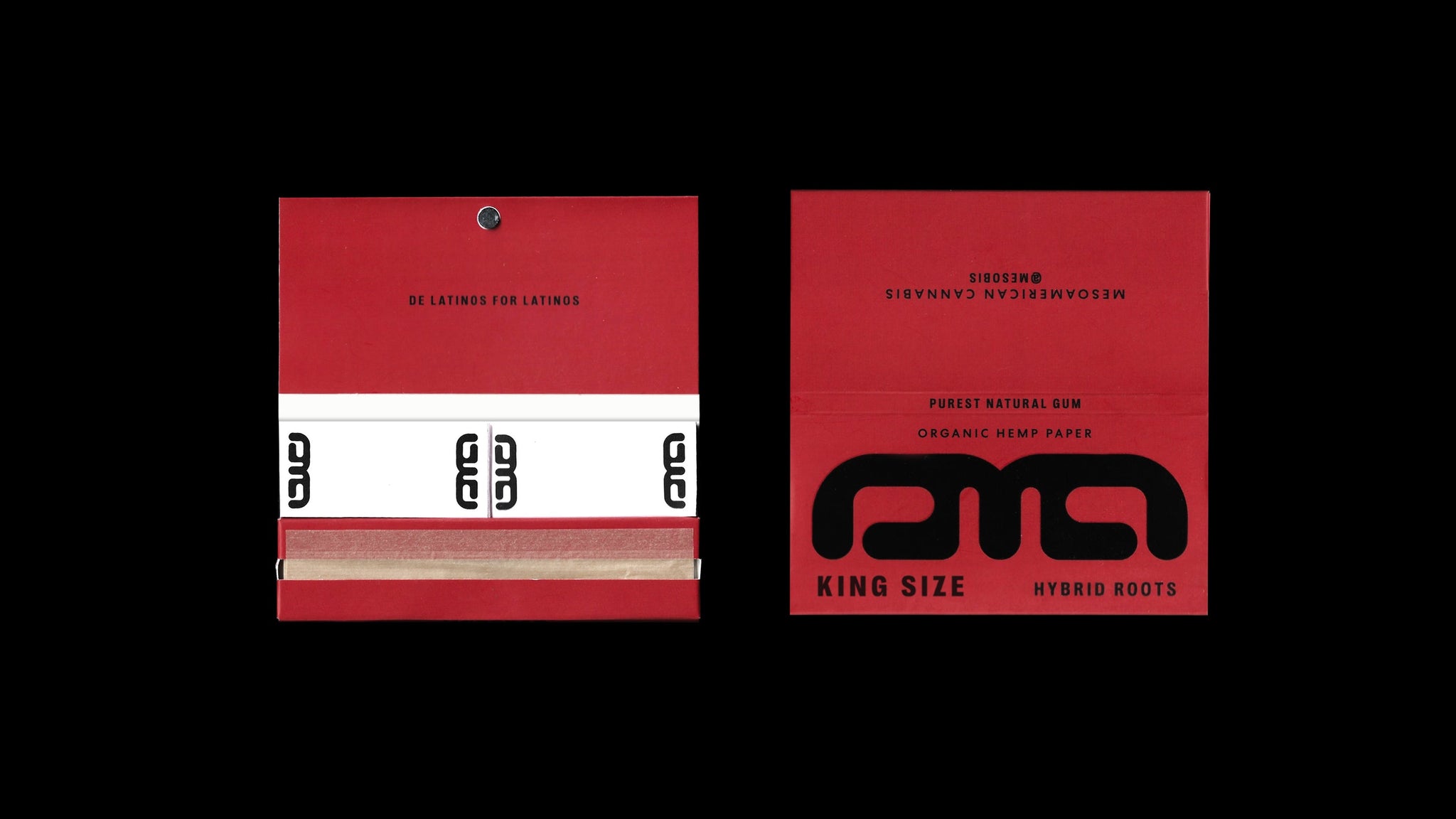
La marque de cannabis Mesobis, basée à Los Angeles, a été créée pour relier les cultures et civilisations californiennes et mésoaméricaines, en combinant des inspirations historiques et brutalistes pour raconter une nouvelle histoire puissante pour l'époque moderne.
Dans le cadre d'une collaboration basée à Mexico avec le studio de design Mad Monk, le designer guatémaltèque Andrés Higueros a entrepris d'incarner visuellement cette entreprise à travers une typographie d'influence maya et de saveur futuriste, armé d'une riche compréhension du contexte de la marque.
« Conformément aux principes de cet art », explique Higueros, en référence à ses racines latino-américaines, « j'ai choisi deux polices de caractères complémentaires », optant pour la Right Grotesk, une police sans empattement Condensede de Pangram Pangram, comme titre principal, aux côtés du logotype sur mesure, imposant et massif. « Right Grotesk s'intègre parfaitement à l'esthétique du logo », explique Higueros, suggérant l'avantage conjonctif et harmonieux de la construction audacieuse et robuste de la police. « Elle équilibre l'esthétique brutaliste de la police personnalisée du logo », poursuit-il, « et les messages de la marque, créant ainsi une marque cohérente », soutenue par l'utilisation de Centra No. 2 de Sharp Type comme police secondaire. « Centra No. 2 est une typographie géométrique qui intègre également des principes brutalistes dans son anatomie », rappelle Higueros, « mais avec une approche tendance », optimisée pour les petits formats de texte grâce à sa nature géométrique.
On retrouve un même discours de simplicité, de praticité et de narration dans la palette de couleurs de Mesobis, le designer ayant opté pour une palette vive qui permet de différencier les produits proposés. « Chaque couleur est liée aux effets du cannabis sur le corps », explique Higueros, précisant que le jaune est énergisant, le rouge passionné, le vert rafraîchissant et le rose relaxant. « Ces couleurs s'inspirent de celles que l'on retrouve dans les pays d'Amérique latine », poursuit-il, comme les vêtements, les paysages et l'art. « Ainsi », conclut Higueros, « chaque aspect de la marque est lié au message principal de son concept », appliquant la philosophie intégrale et historique de Mesobis à la fois en ligne et sur le marché physique.